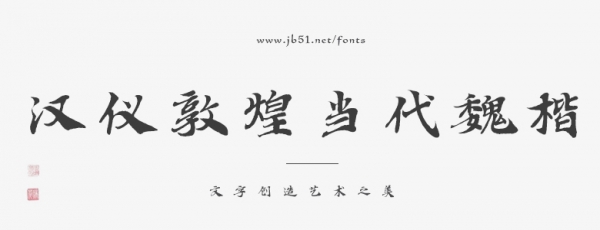
汉仪敦煌当代魏楷秉持“修旧如旧”的设计理念,以北魏魏楷为骨、敦煌写经为韵,着重呈现隶书楷化过程中的关键特征。既还原敦煌写经原生风貌,又适配现代用字需求。
汉仪敦煌当代魏楷在保留写经灵动笔法与沉雄浑厚历史质感的同时,在规范用字与古籍原貌间取得平衡,使千年写经艺术在当代得以传承。该字体适用于北魏时期历史专著、敦煌学研究丛书、敦煌IP文创产品、北魏题材影视视觉物料、佛教文史读物、书画展览及文化赛事等多元场景。以兼具骨力与温度的笔墨气韵传递东方书法之美,满足传统文化与当代设计融合的多元审美需求。